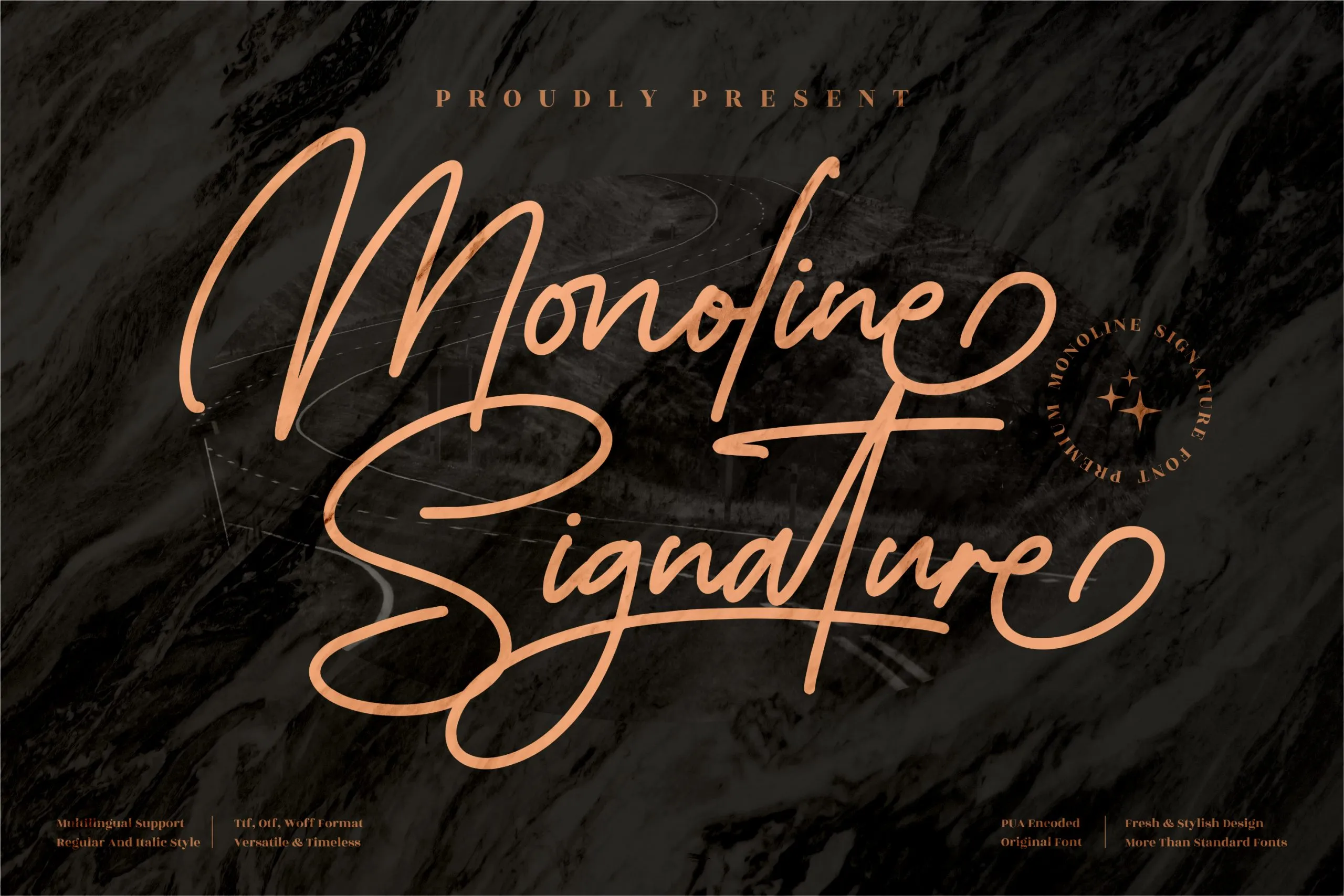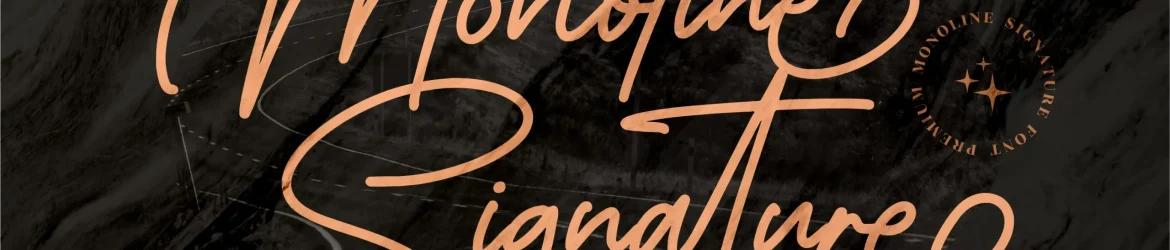
Monoline Signature Font – Download Grátis
A Monoline Signature Font é uma escolha excepcional para qualquer projeto que exija um toque sofisticado e profissional. Com sua linhas elegantes e detalhes suaves, essa fonte idealmente se destina a logos, projetos de marca, design de casa, embalagens de produtos, taças, cartazes, sacolas de compras, cartões de felicitações, folhas de convite, capa de livro, etiquetas e até mesmo fotos. Ela é perfeita para qualquer projeto em que você deseja dar um toque de sofisticação. Seja um evento especial ou uma publicação de alta qualidade, esta fonte Monoline Signature trará um gosto premium à sua criação. É uma escolha atraente para designers e criativos buscando agregar valor com um design único e impecável.